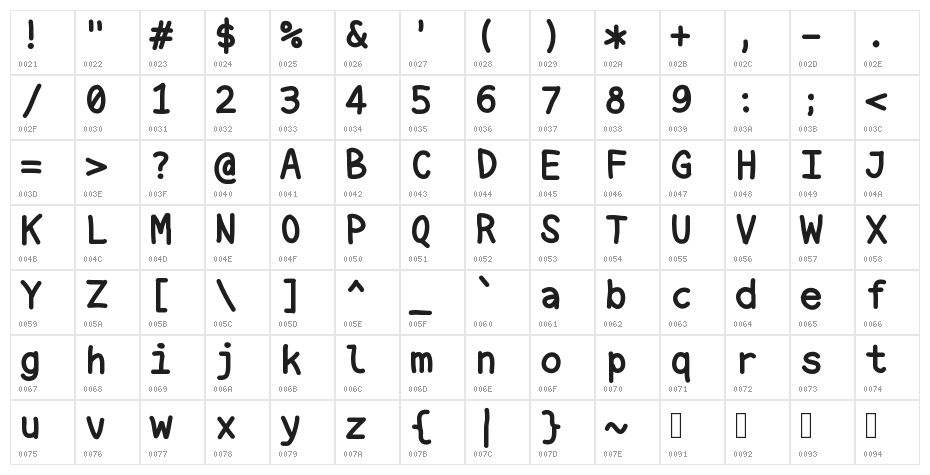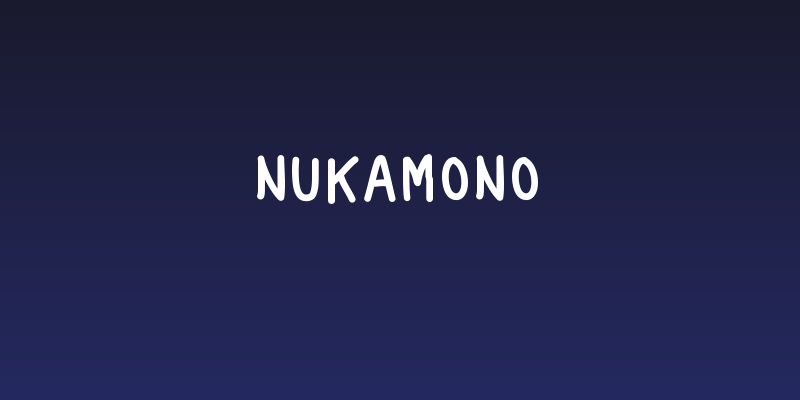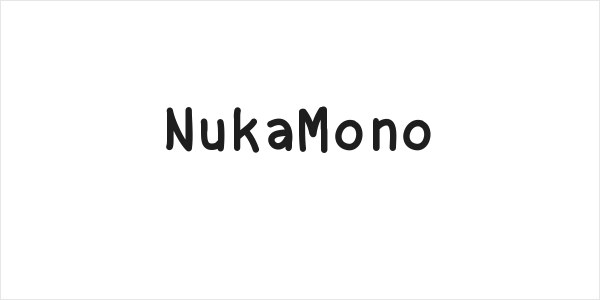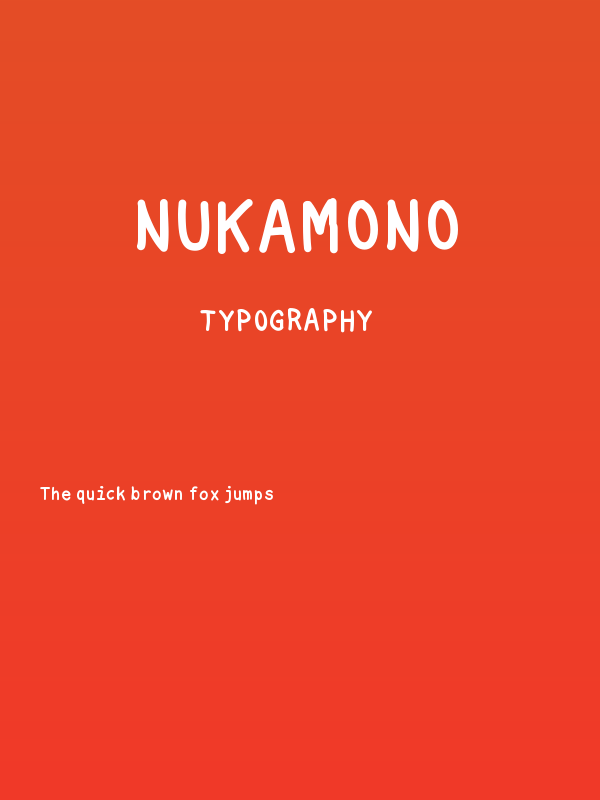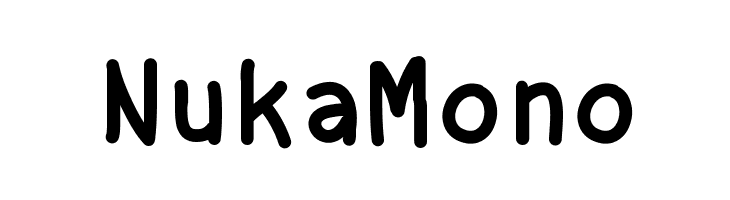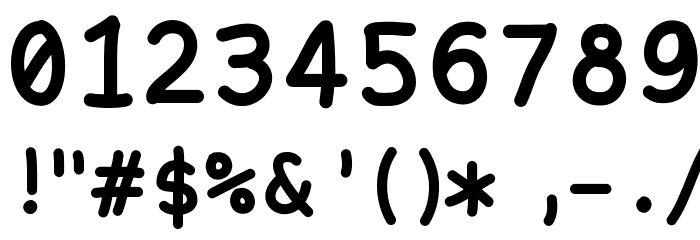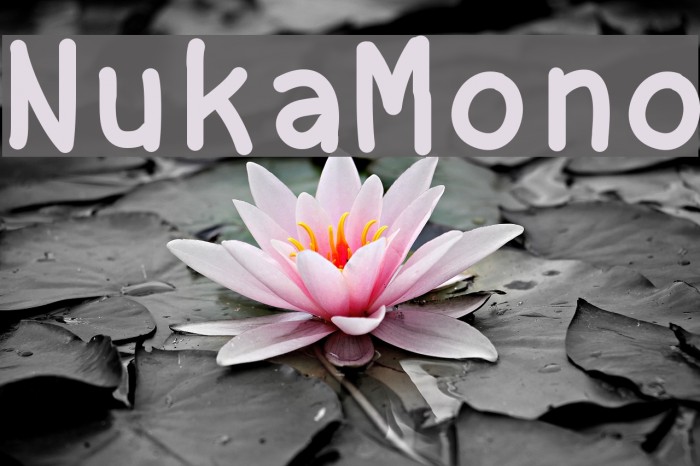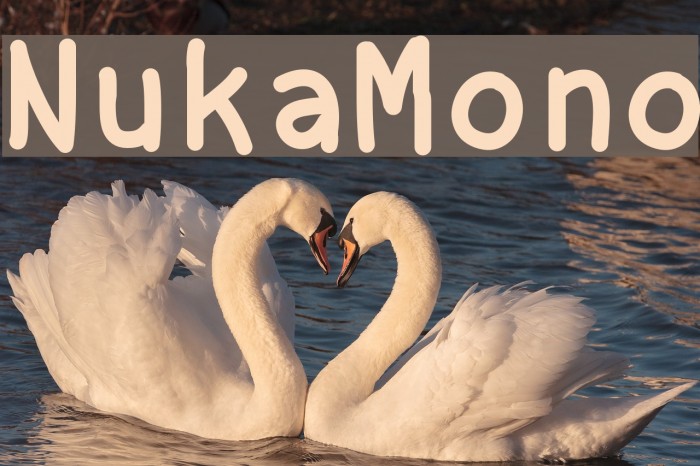
NukaMono Font
| Gesamtstil | Casual |
| Anwendungsfall | Headlines, Logos, Informal Text |
| Vorgeschlagene Projekte | Ideal for children's books, casual branding, playful posters, and informal digital content. |